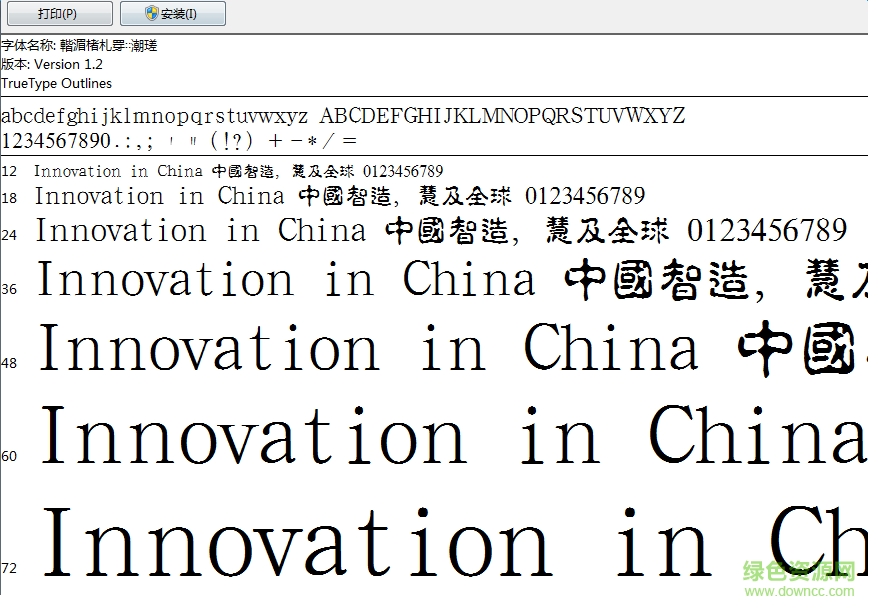
漢儀繁淡古是一款古典風(fēng)格字體軟件,繁淡古體筆畫繁瑣,粗細(xì)相間,整體效果非常顯眼,還有更多好看字體下載歡迎來綠色資源網(wǎng)!
漢儀繁淡古是一款應(yīng)用于藝術(shù)設(shè)計(jì)方面的簡體中文字體,該字體筆畫粗壯,尾部的甩尾有力且有豐富的筆觸細(xì)節(jié),大字效果突出且引人注目;并且最大程度還原作者書寫字形,細(xì)節(jié)表現(xiàn)完整,且字庫完整,可以廣泛應(yīng)用于名片設(shè)計(jì)、新聞媒體、宣傳海報(bào)、ppt、影視制作以及內(nèi)容用字等領(lǐng)域。
漢儀繁淡古字體適用于繁體文章書寫應(yīng)用,該字體非常經(jīng)典古老,盡顯中國文學(xué)字體的魅力,歡迎下載使用!